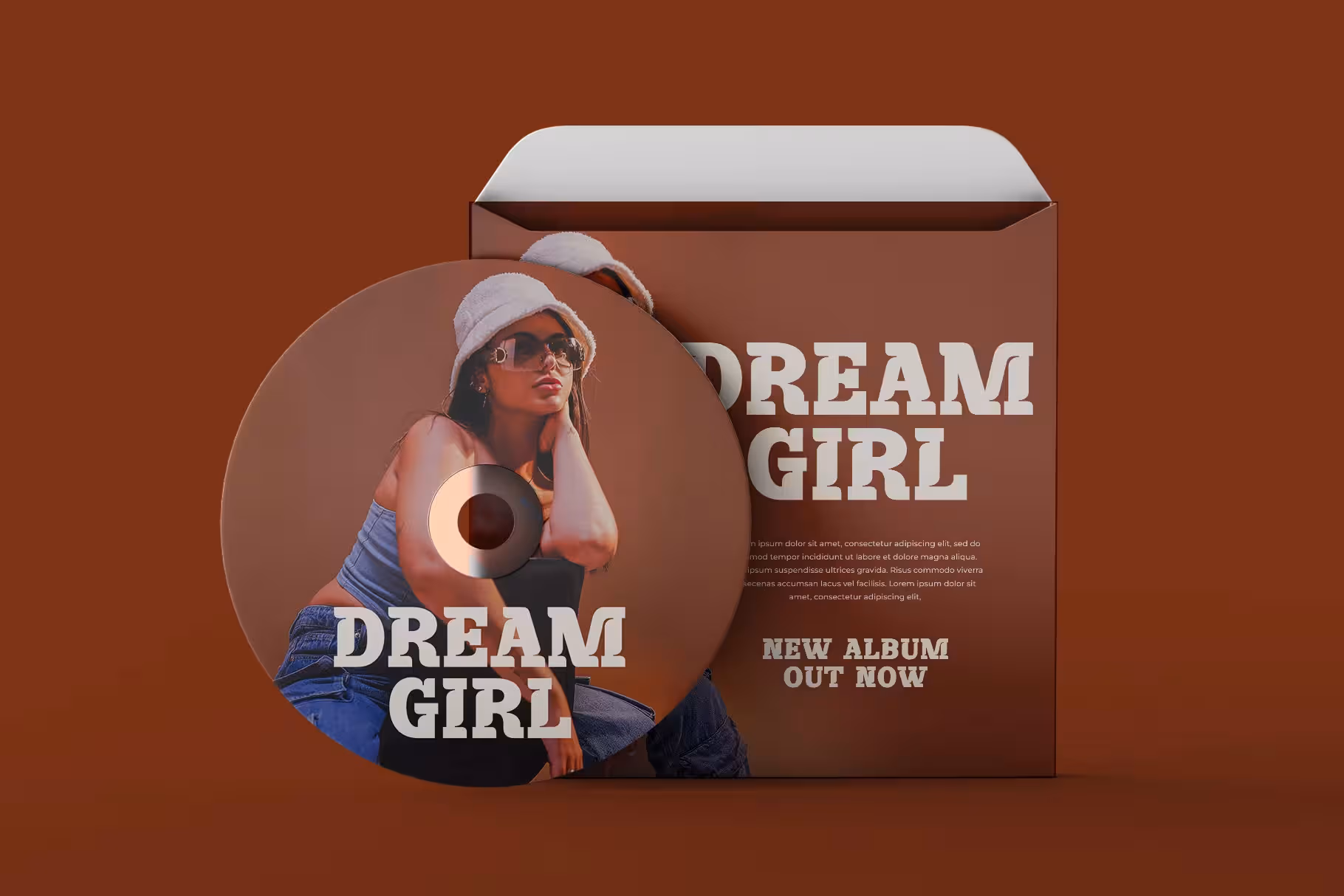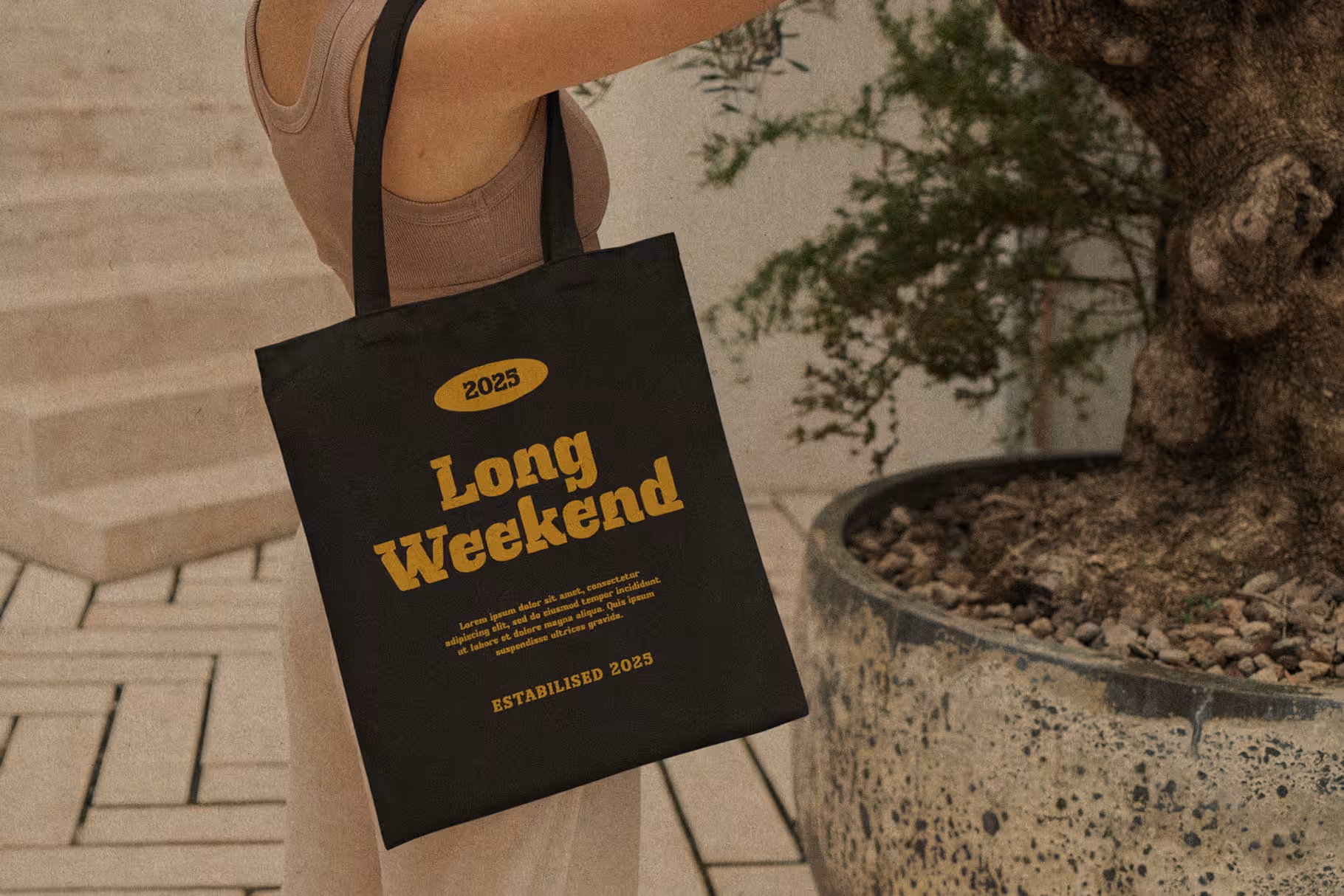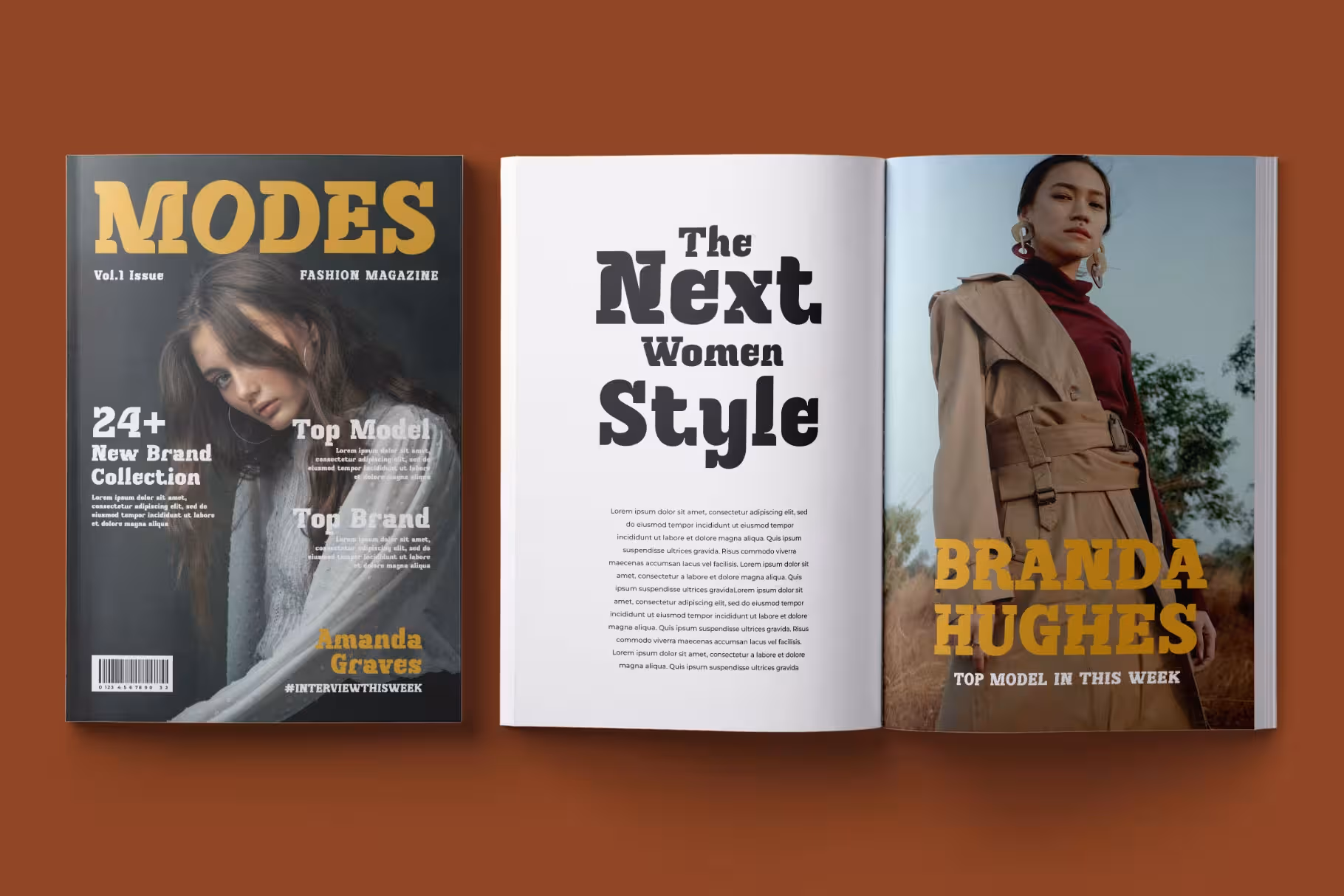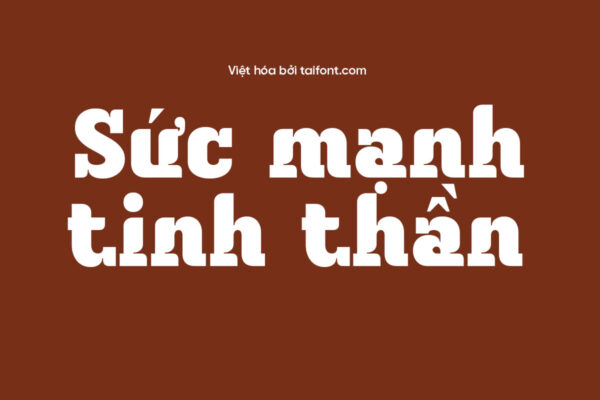
Giới thiệu về Font TF Recilda Việt hóa
TF Recilda Việt hóa là một font chữ trang trí nổi bật với vẻ đẹp tinh tế, độc đáo và đầy phong cách. Font này mang đến sự pha trộn hài hòa giữa nét thanh lịch và sự cá tính, tạo cảm giác như một tác phẩm nghệ thuật được chăm chút tỉ mỉ. Với những đường nét duyên dáng và một chút biến tấu, Recilda lý tưởng để tạo điểm nhấn đặc biệt và thu hút mọi ánh nhìn.
Với đặc điểm thiết kế độc đáo và khả năng tạo ấn tượng mạnh mẽ, Recilda là lựa chọn lý tưởng cho các thiết kế muốn truyền tải sự tinh tế, độc đáo và phong cách:
- Thiết kế thời trang: Hoàn hảo cho các thương hiệu thời trang muốn thể hiện sự độc quyền và đẳng cấp. Font có thể được sử dụng cho logo, nhãn mác sản phẩm, in ấn trên trang phục hoặc các chiến dịch quảng bá bộ sưu tập. Nét chữ độc đáo của Recilda sẽ giúp nâng tầm giá trị thương hiệu và tạo dấu ấn riêng biệt trong ngành thời trang.
- Thiết kế túi vải (tote bag, canvas bag): Lý tưởng để in các tên thương hiệu, slogan, hoặc các họa tiết chữ lên túi vải canvas. Nét trang trí của font sẽ làm cho chiếc túi trở nên cá tính, phong cách và thu hút sự chú ý.
- Thiết kế nhận diện thương hiệu: Phù hợp cho các logo, tagline hoặc bộ nhận diện thương hiệu muốn truyền tải sự tinh tế, hiện đại và một chút nghệ thuật.
- Thiết kế bao bì sản phẩm: Có thể dùng cho các sản phẩm thủ công, đặc sản địa phương, hoặc các mặt hàng muốn truyền tải sự độc đáo và chất lượng.
Với TF Recilda Việt hóa, bạn có thể dễ dàng thổi hồn tinh tế, sự độc đáo và phong cách vào các thiết kế, tạo ra những sản phẩm không chỉ đẹp mắt mà còn đầy cảm xúc và sức hút đặc biệt.
Font Việt hóa TF Recilda